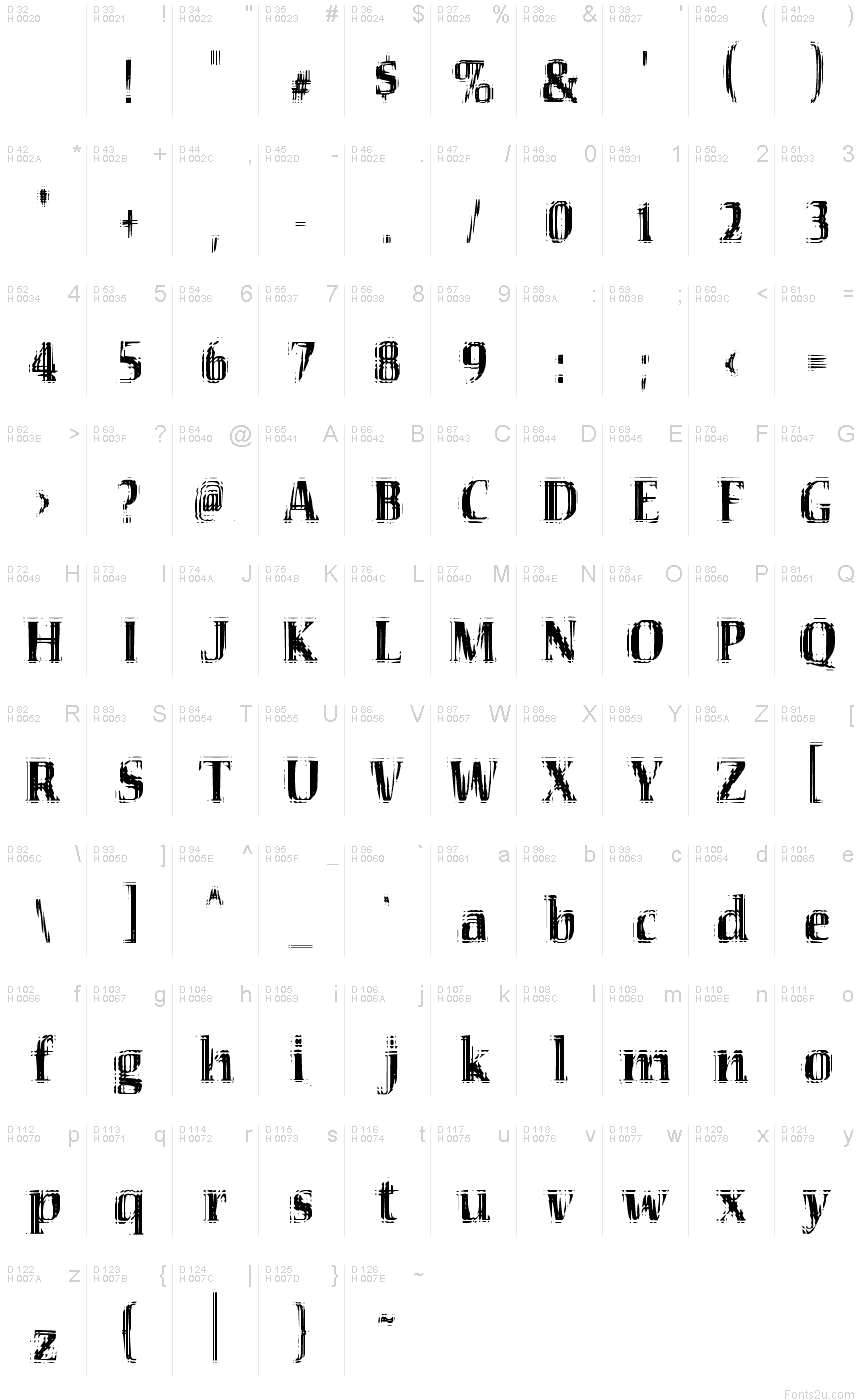
VTC Seeindubbledointriple Regular
تعد VTC Seeindubbledointriple من VigilanteTypeface Corporation خطاً مجانياً مشوهاً للعناوين (Display font)، يتميز بمظهر مطبوع وممزق يجمع بين روح ملصقات الـ «جرونج» وجماليات الطباعة الخشبية المتضررة. تتمتع الحروف بأشكال عمودية ثقيلة وحواف مكررة ومزاحة، لتبدو كأنها حبر قد انزلق وتضاعف وتمزق أثناء طباعته على الصفحة.
هذا الصدى الخشن يجعل الخط خياراً طبيعياً لمجلات الـ «زين»، ومنشورات الحفلات، وعناوين أفلام الرعب، وأغلفة الأسطوانات، والعلامات التجارية التي تميل للأجواء الغامضة، حيث تكون الحاجة إلى لمسة من الاهتراء البصري ضرورية. كخط مجاني، يعمل بشكل مثالي في النصوص القصيرة ذات التأثير العالي مثل عناوين الغلاف، وبطاقات العناوين، أو الشعارات، حيث يمكن لتأثيرات التضاعف والظلال الثلاثية أن توصل الرسالة بسرعة.